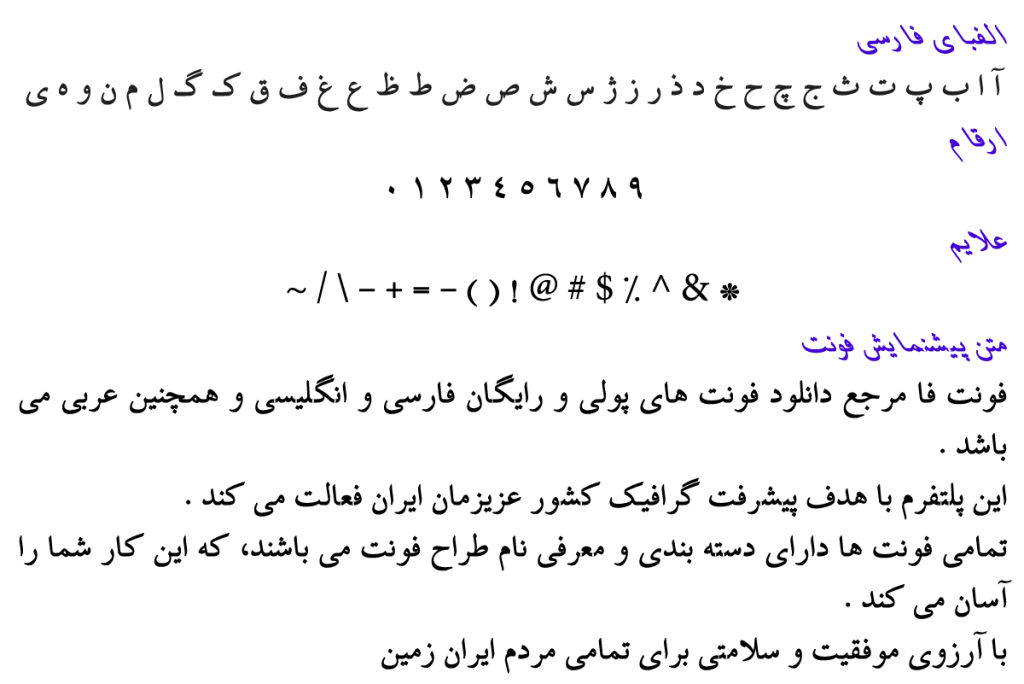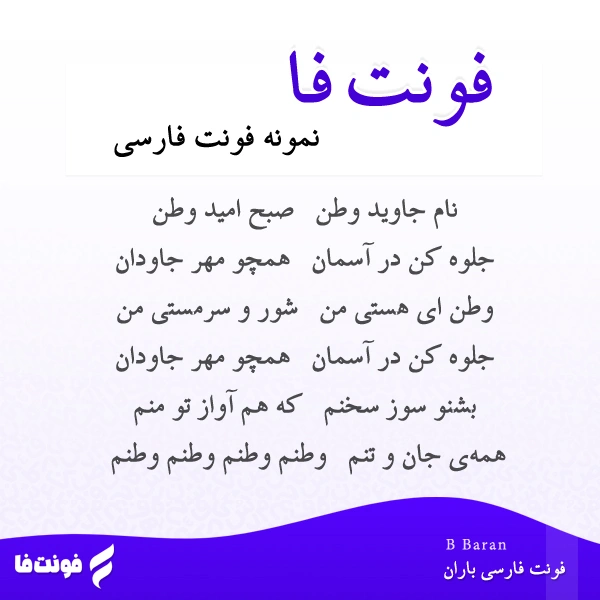
فونت فارسی باران – B Baran
سال ساخت فونت: 1379
مجموعه فونت: فونت سری B
طراح فونت: برنا رایانه نوع فونت: فونت متن
پیشنمایش فونت بی باران
توضیحات و معرفی فونت باران
فونت فارسی باران ( B Baran ) از مجموعه فونت های سری B می باشد، و نیز نوع فونت متن می باشد.
فونت خوشگل مربوط توسط برنا رایانه در سال 1379 طراحی و ساخته شده است.
لیست وزن و فرمت های فونت B Baran
و نیز فونت B Baran در 3 وزن معمولی و کج و توخالی خطی است.
در لیست زیر می توانید وزن های این فونت خوشگل را ببینید.
- B Baran Regular
- B Baran Italic
- B Baran Outline
شعر میهنی زیر با این تایپ فیس طراحی شده و نمایانگر زیبایی آن است.